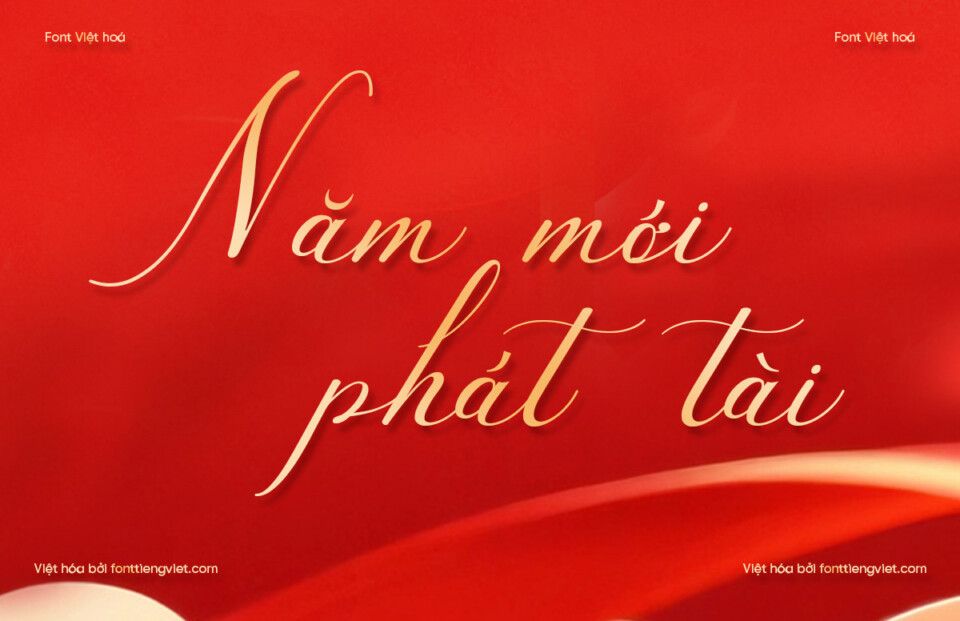
Font Việt hóa 1FTV VIP Aurelia Marcelina Font tết
Giới thiệu về Font Việt hóa 1FTV VIP Aurelia Marcelina Font tết
Trong không khí rộn ràng của những ngày giáp Tết, việc tìm kiếm một bộ Font Miễn Phí chất lượng để thiết kế bao lì xì, thiệp chúc mừng hay băng rôn sự kiện là ưu tiên hàng đầu của nhiều bạn học sinh và thầy cô giáo. Font Việt hóa 1FTV VIP Aurelia Marcelina Font tết xuất hiện như một giải pháp hoàn hảo, mang đến vẻ đẹp thanh lịch nhưng không kém phần rực rỡ cho mọi ấn phẩm truyền thông. Đây là một bộ font thuộc phân khúc cao cấp đã được đội ngũ 1FTV tinh chỉnh kỹ lưỡng, giúp người dùng dễ dàng gõ tiếng Việt có dấu mà không lo bị lỗi hiển thị. Với những đường nét uốn lượn mềm mại và phong cách bay bổng, bộ chữ này rất phù hợp để truyền tải những lời chúc an khang và thịnh vượng trong dịp Tết Nguyên Đán truyền thống.
Đặc điểm nổi bật của Font Việt hóa 1FTV VIP Aurelia Marcelina
Bộ Font Việt hóa 1FTV VIP Aurelia Marcelina Font tết sở hữu những đặc điểm nhận dạng độc đáo không lẫn vào đâu được. Đầu tiên là hệ thống các ký tự thay thế (alternates) và các nét chữ nối (ligatures) vô cùng đa dạng, cho phép người dùng sáng tạo ra những tiêu đề bắt mắt. Đường nét của Aurelia Marcelina mang tính chất viết tay điêu luyện, tạo cảm giác thân thiện và gần gũi như những dòng chữ thư pháp hiện đại. Đặc biệt, bộ font này đã được tối ưu hóa độ dày nét chữ để khi in ấn trên các chất liệu giấy mỹ thuật hoặc bạt hiflex vẫn giữ được độ sắc nét tuyệt đối. Đối với các bạn học sinh đang học thiết kế đồ họa cơ bản, đây là một công cụ hỗ trợ tuyệt vời để tạo nên những bài thuyết trình hoặc poster lớp đầy ấn tượng.
Ứng dụng Font Việt hóa 1FTV VIP Aurelia Marcelina Font tết trong thiết kế
Không chỉ giới hạn trong các thiết kế liên quan đến lễ hội, Font Việt hóa 1FTV VIP Aurelia Marcelina Font tết còn rất linh hoạt trong nhiều bối cảnh khác nhau. Bạn có thể sử dụng bộ font này để làm tiêu đề cho các video TikTok về chủ đề xuân, hay thiết kế các hình ảnh chúc mừng năm mới trên Facebook và Instagram. Trong môi trường học đường, giáo viên có thể dùng font chữ này để làm trang trí bảng tin hoặc các giấy khen cuối học kỳ một nhằm khích lệ tinh thần học tập của học sinh. Sự kết hợp giữa nét chữ nghệ thuật và tính ứng dụng cao giúp cho Aurelia Marcelina trở thành sự lựa chọn số một cho các dự án sáng tạo cần sự tinh tế.
Lưu ý khi sử dụng font chữ trong thiết kế Tết
Để phát huy tối đa vẻ đẹp của Font Việt hóa 1FTV VIP Aurelia Marcelina Font tết, người thiết kế nên kết hợp với những gam màu chủ đạo của mùa xuân như đỏ may mắn, vàng kim thịnh vượng hoặc xanh lá của sự đâm chồi nảy lộc. Bạn nên sử dụng font này cho các cụm từ ngắn như “Chúc Mừng Năm Mới”, “Vạn Sự Như Ý” để tạo điểm nhấn thị giác mạnh mẽ. Tránh sử dụng font dạng viết tay này cho các đoạn văn bản dài vì sẽ gây mỏi mắt cho người đọc. Một mẹo nhỏ là hãy thử kết hợp nó với một font chữ không chân (sans-serif) đơn giản để tạo ra sự cân bằng cho bố cục tổng thể của tác phẩm.
Việc lựa chọn các sản phẩm từ 1FTV luôn đảm bảo cho người dùng về độ chuẩn hóa của bảng mã Unicode. Các dấu tiếng Việt được đặt ở vị trí hợp lý, không bị quá cao hay quá thấp, giúp văn bản trông cân đối và chuyên nghiệp hơn. Ngoài ra, việc chia sẻ rộng rãi những bộ font chất lượng như thế này giúp cộng đồng sáng tạo tại Việt Nam ngày càng phát triển mạnh mẽ hơn.
Kết luận